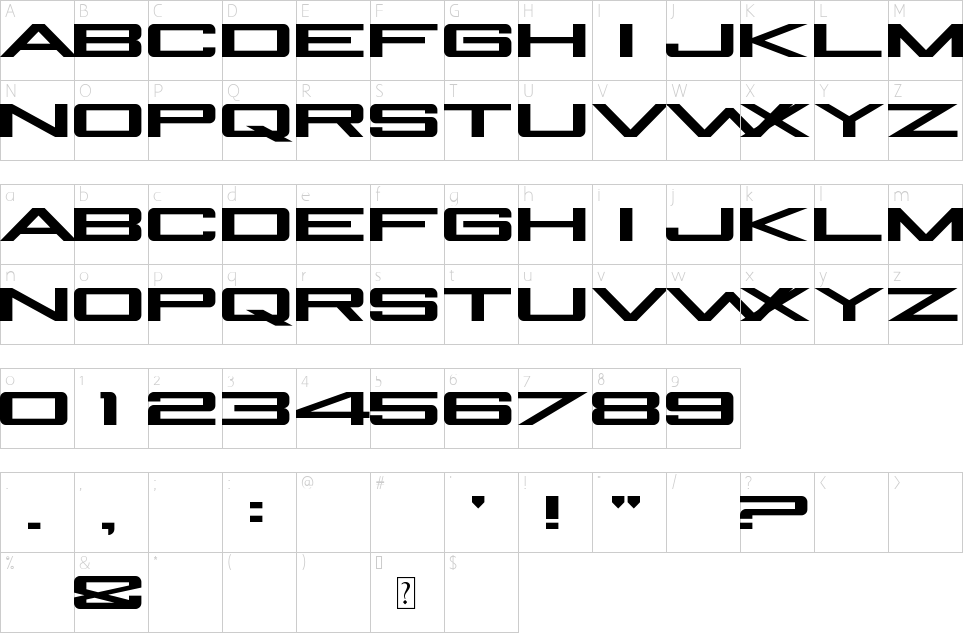
Aqui está uma versão do texto para a página de download da font ‘Be A Pro Font’: Aqui está uma nova adição ao seu arsenal de ferramentas digitais: ‘Be A Pro’, uma elegante e minimalista font que vai dar um toque especial às suas criações. Desenvolvida por Jayde Garrow, esta font tem sido descarregada 7,156 vezes pelo público global. ‘Be A Pro’ é perfeita para qualquer criatividade digital – seja você um designer gráfico, um editor de conteúdo ou até mesmo alguém que simplesmente adora criar. Seja na versão Windows ou Mac, a ‘Be A Pro Font’ oferece facilidades para usar em sua próxima obra-prima. Não importa o tipo de projeto: seja uma imagem de logotipo, design de produtos ou qualquer outro formato digital – a font ‘Be A Pro’ terá seu lugar. Com um design simples e limpo, ela trará uma nova dimensão ao seu trabalho final. Descarregue agora sua cópia da ‘Be A Pro Font’ para começar a criar algo que realmente faça a diferença. Essa é uma fonte gráfica de alta qualidade com um preço justo. Não deixe essa oportunidade passar!